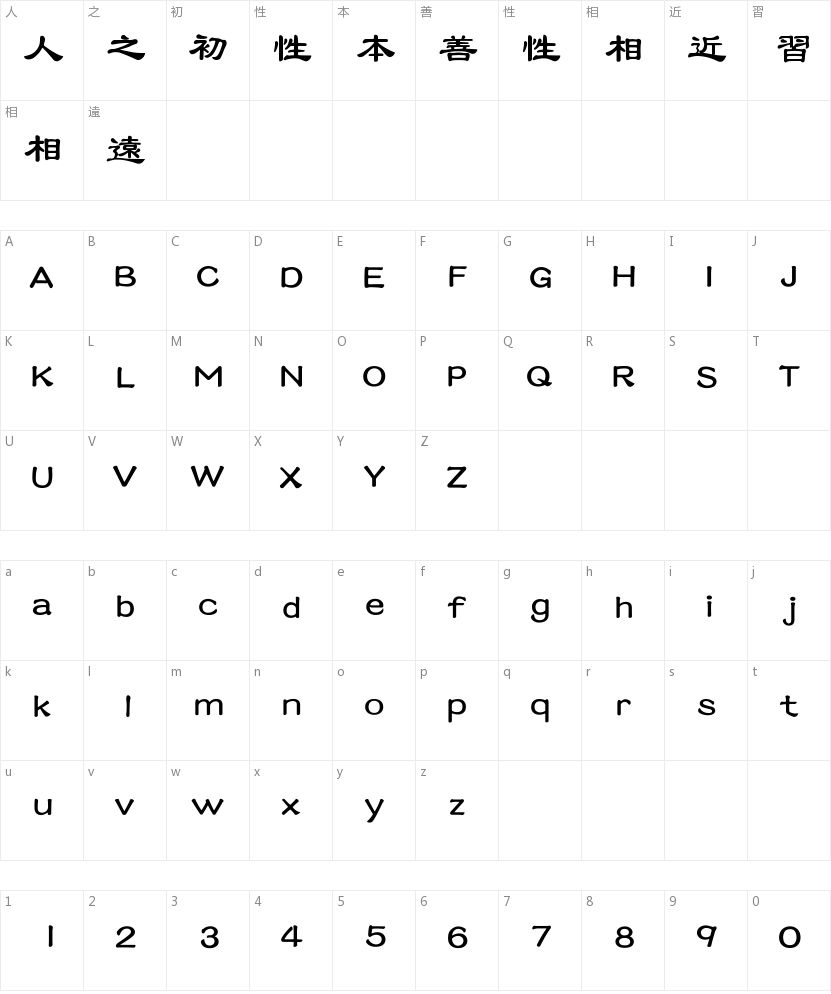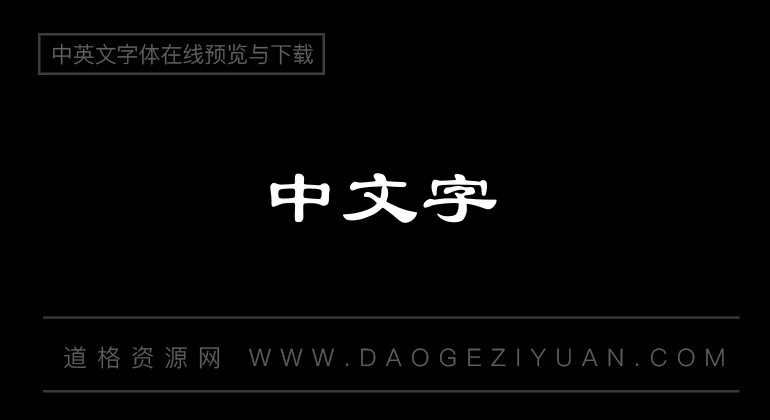
蒙纳繁古隶
蒙纳繁古隶是一款由Mingtiandy字体工作室设计的繁体字字体,它是一款汉字字体,以古典的繁体字为主,以现代的设计理念为设计基础,具有浓郁的中国古典风格。蒙纳繁古隶字体以精致、优雅、柔和的线条,体现古典文化的高贵气质,具有极高的视觉冲击力,是您文字艺术设计的不二之选。
蒙纳繁古隶是一款非常不错的手写艺术字体,具有很好的视觉感,适合于文化类的宣传设计、商业类品牌的广告和产品包装设计以及个性化文字排版等较多场景。